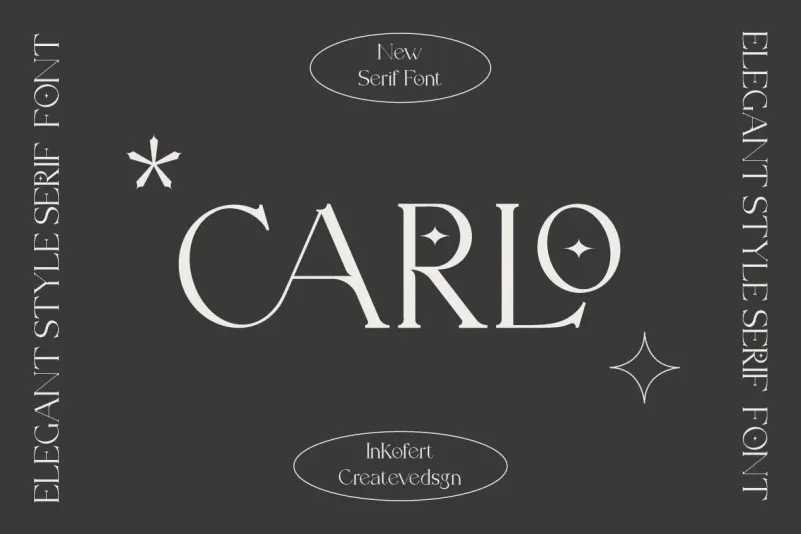
Este é ‘Carlo Font’, uma elegante fuente serif que transmite sofisticação e elegância, criando impressionantes logotipos, citações, postagens em blogs, marcas de marca, imagens de revistas, convites para casamentos e apresentações. O design cuidadosamente elaborado proporciona um toque refinado para qualquer projeto visual. ‘Carlo Font’ é perfeito para quem busca uma fuente com forte impacto que se destaca no mundo dos materiais gráficos. Estendendo ainda mais o alcance de suas possibilidades, este elegante tipo de texto transmite sua presença sóbria em todas as aplicações. Seja em sites profissionais, impressões de revistas ou em cartões de convite para casamentos, ‘Carlo Font’ é uma escolha inteligente para qualquer projeto que deseje um visual impressionante e sofisticado.